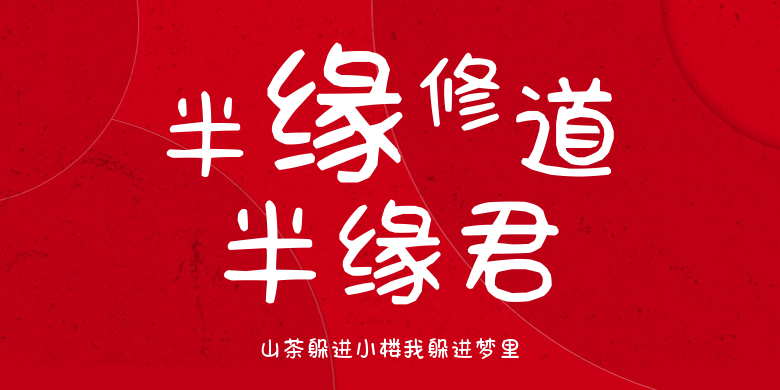
山茶躲进小楼我躲进梦里
山茶躲进小楼我躲进梦里,这款字体结构工整、笔画清晰,兼顾美观与易读性,适用于标题、正文、海报、包装、LOGO 等多种场景。字形优雅稳定,风格百搭耐看,适配日常排版与创意设计,让文字呈现更舒适、更具质感。山茶躲进小楼我躲进梦里一笔一画,皆是细节,以均衡的比例、流畅的线条打造舒适视觉体验,字形端正大气,风格简约现代。无论是商业设计、品牌宣传还是日常排版,都能轻松驾驭,让文字更有格调与力量。山茶躲进小楼我躲进梦里字体下载。